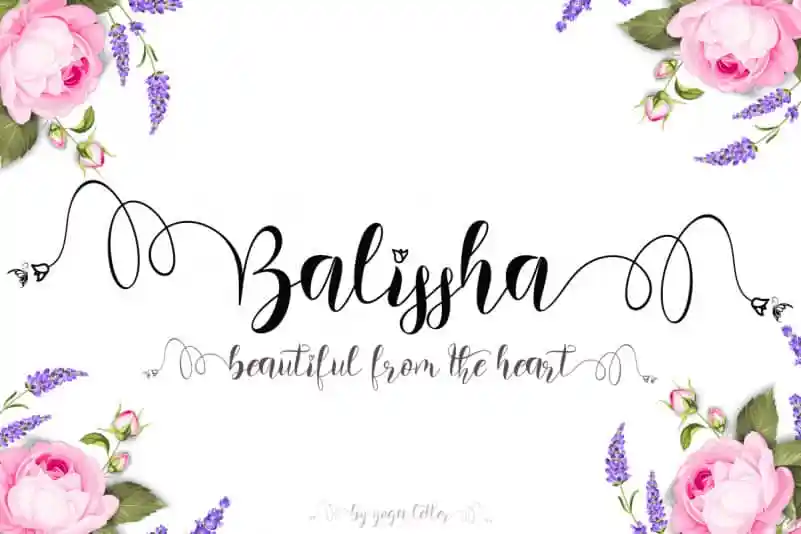
Balissha Calligraphy Font – Download Grátis
Balissha Calligraphy Font é uma excelente escolha para quem procura uma fonte de estilo chinesa delicado e sofisticada, perfeitamente adaptável a diversas aplicações. Especificamente projetada para atender aos requisitos específicos do mundo dos noivados, esta fonte está repleta de elegância e charme, ideal tanto para invitations casais quanto para trabalhos decorativos relacionados ao casamento. Além disso, Balisha Calligraphy é perfeitamente adequado para promoções variadas. Suas linhas finas e sutis se adaptam perfeitamente a qualquer tipo de negócio ou produto que você deseja promover. Este fonte também é uma ótima opção para criar logotipos, identidade visual e materiais publicitários, seja para um hotel de luxo, um resort deslumbrante ou até mesmo para produtos e serviços. Além disso, Balisha Calligraphy está sempre em sintonia com as festividades do Natal e da primavera, adicionando um toque especial às suas mensagens. Com o Balisa Calligraphy Font, você pode se surpreender não apenas com sua beleza visual, mas também com a facilidade de uso. Esse font é uma verdadeira joia para todos os profissionais que buscam trazer uma sensação única e sofisticada em seus projetos digitais.